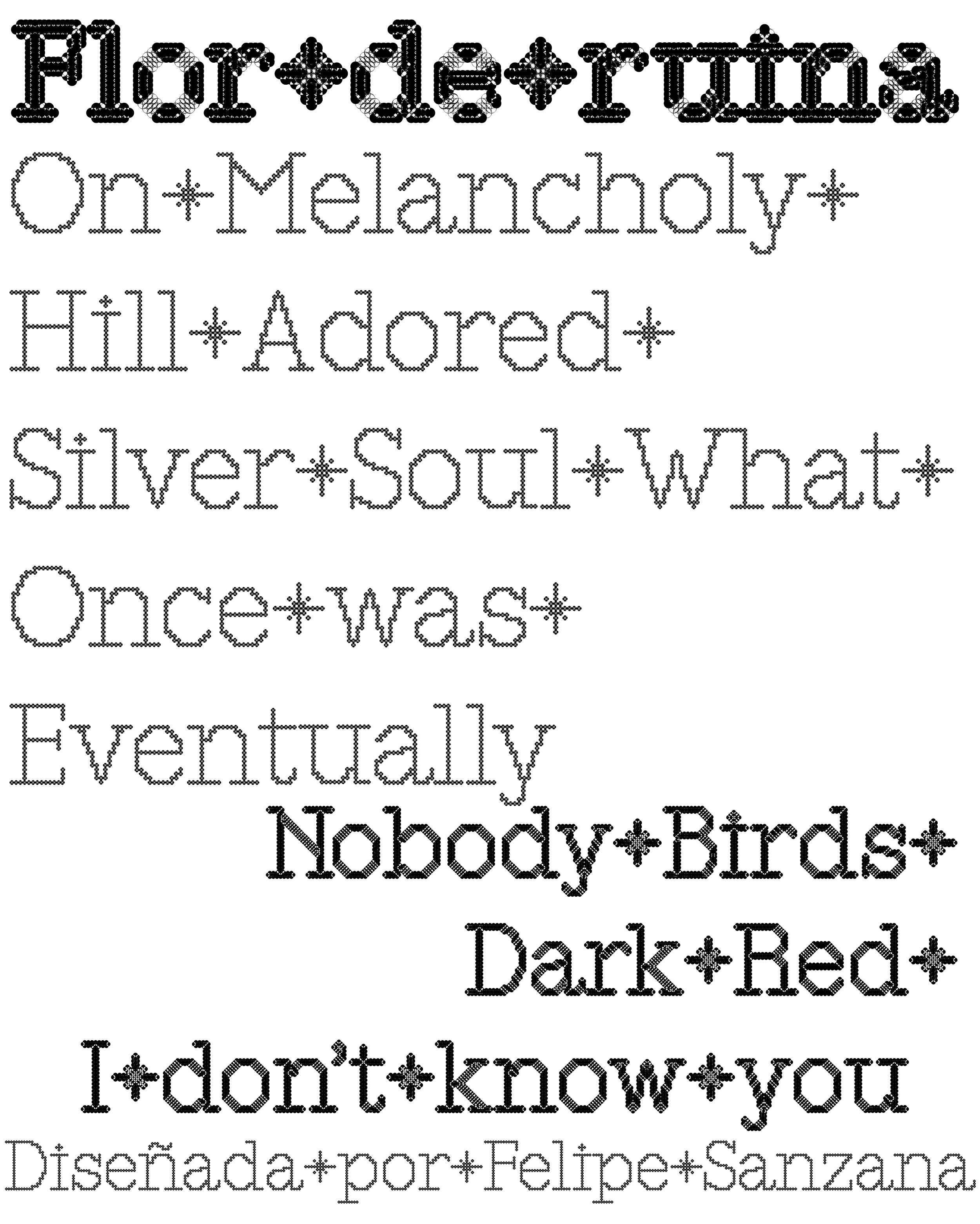
| Descripción | Flor de ruina, nacida desde la fractura. Artefacto tipográfico. Cada glifo brota en grieta en ruina. Esta tipografía es un artefacto impotente ante la violencia, sin embargo, insiste como herramienta para visibilizar el dolor, la intolerancia, la violencia, y los crímenes humanitarios. |
| Familia(s) | Ruina, Semilla, Flor |